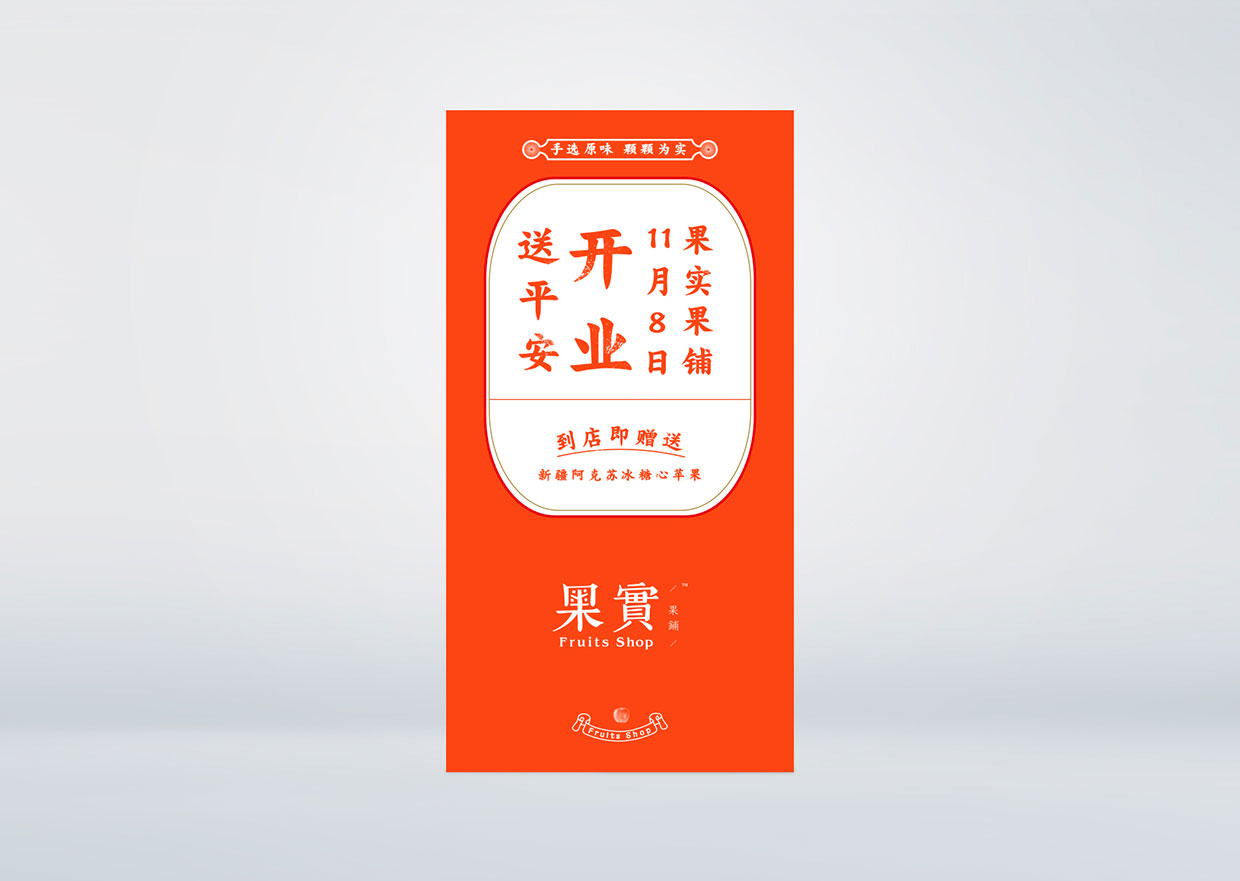
果实果铺/Fruits Shop品牌设计字体设计赏析
果实果铺/Fruits Shop品牌设计字体设计赏析,这款字体结构工整、笔画清晰,兼顾美观与易读性,适用于标题、正文、海报、包装、LOGO 等多种场景。字形优雅稳定,风格百搭耐看,适配日常排版与创意设计,让文字呈现更舒适、更具质感。果实果铺/Fruits Shop品牌设计字体设计赏析一笔一画,皆是细节,以均衡的比例、流畅的线条打造舒适视觉体验,字形端正大气,风格简约现代。无论是商业设计、品牌宣传还是日常排版,都能轻松驾驭,让文字更有格调与力量。果实果铺/Fruits Shop品牌设计字体设计赏析字体下载。